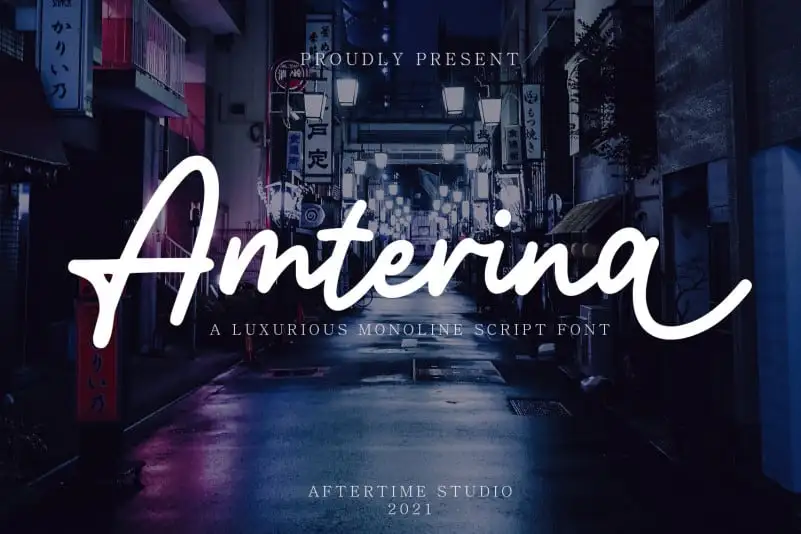
Amterina – Monoline Script Font – Download Grátis
A Amterina é uma fonte simples que se destaca pela sua elegância, legibilidade e estilo distintivo. Oferece alternativas de letras e ligaturas para torná-la ainda mais versátil e atraente. Esta fonte é perfeita tanto para o design de watermark em fotografias como para criar assinaturas ou logotipos de assinatura, além de ser ótima para aplicações como citações, capas de álbuns, cartões de empresa e muitos outros projetos de design. Sua simplicidade e versatilidade a tornam uma opção ideal para aqueles que procuram um detalhe cuidadosamente pensado em seus trabalhos gráficos.